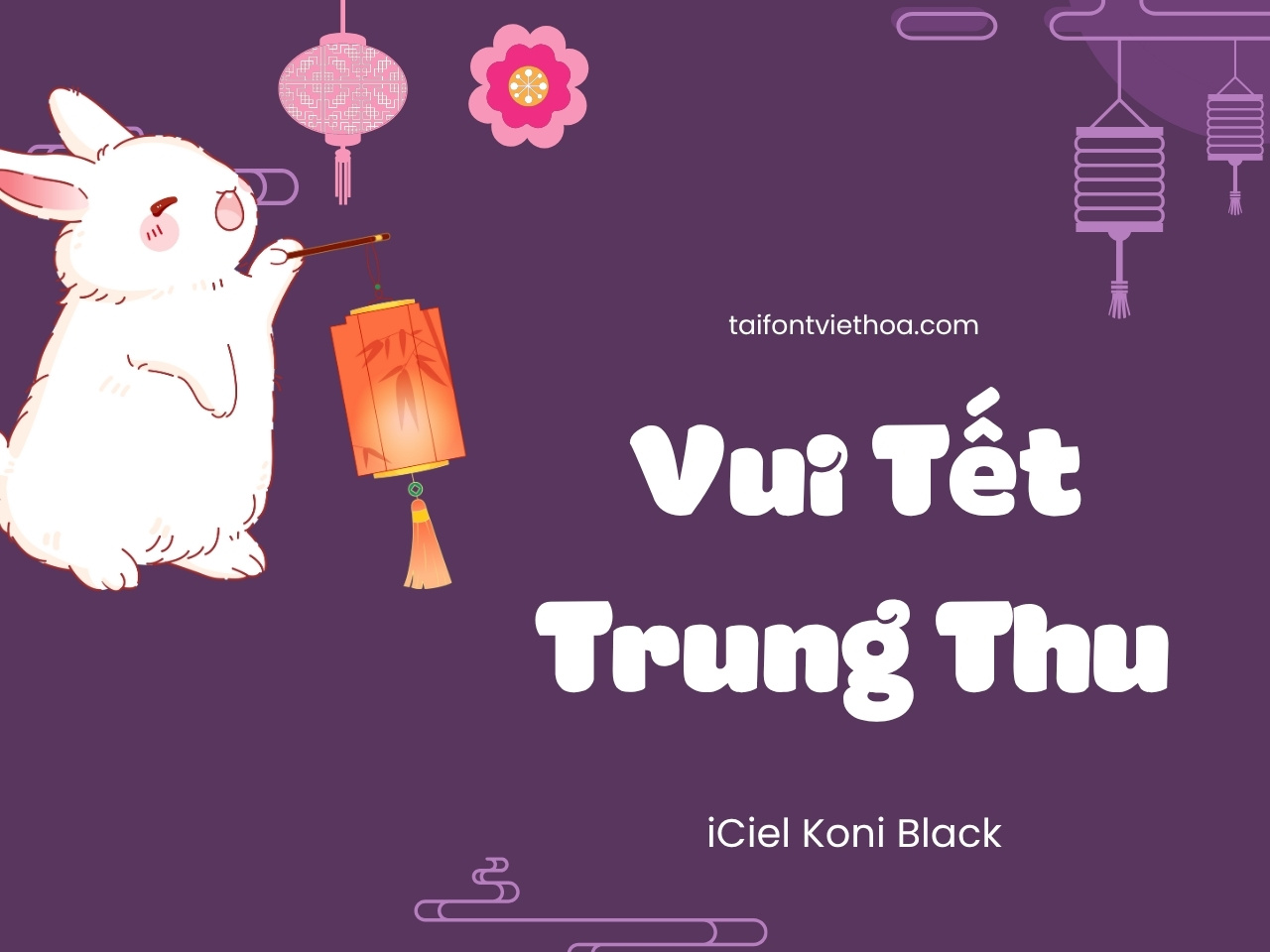
Font việt hóa iCiel Koni
Giới thiệu về font iCiel Koni – Tươi mới, hiện đại và đầy tính thương hiệu
iCiel Koni là một kiểu chữ sans-serif kết hợp phong cách display độc đáo, được thiết kế theo hướng hiện đại, trẻ trung và đậm chất thương hiệu. Font được Việt hóa bởi iCiel, hỗ trợ đầy đủ tiếng Việt cùng hơn 60 ngôn ngữ khác, phù hợp cho các nhà thiết kế đang tìm kiếm giải pháp typography nổi bật cho bao bì, logo, tiêu đề và chiến dịch quảng bá sáng tạo.
Font được taifontviethoa.com chọn lọc kỹ lưỡng nhằm mang đến một lựa chọn đậm tính cá nhân và mang hiệu quả truyền thông mạnh. iCiel Koni đã được ứng dụng thực tế trong nhiều dự án thiết kế liên quan đến thực phẩm, đồ uống, thời trang trẻ hoặc ngành giải trí. Với form chữ chắc chắn, bo góc mềm mại và cấu trúc thân thiện, Koni mang lại trải nghiệm thị giác dễ chịu nhưng vẫn thu hút mạnh mẽ.
Đặc điểm thiết kế và ứng dụng nổi bật của font iCiel Koni
iCiel Koni sở hữu nét chữ sans-serif không chân, với các ký tự đậm nét, tròn trịa và đường bo mượt mà. Thiết kế hướng đến sự tối giản nhưng không khô cứng, kết hợp giữa nét trẻ trung và sự chuyên nghiệp. Nhờ độ đậm cao và tỷ lệ chữ cân đối, font đặc biệt hiệu quả khi sử dụng làm tiêu đề, logo hoặc slogan quảng cáo cần sự nổi bật và dễ ghi nhớ.
Font này phù hợp với nhiều ngành nghề như ẩm thực, thời trang trẻ, đồ uống, sản phẩm handmade, giáo dục hoặc startup sáng tạo. Ứng dụng tiêu biểu gồm: thiết kế bao bì snack – nước giải khát, logo thương hiệu hiện đại, banner sự kiện, poster nghệ thuật, bảng hiệu cửa hàng hoặc nội dung mạng xã hội hướng đến giới trẻ năng động và cá tính.